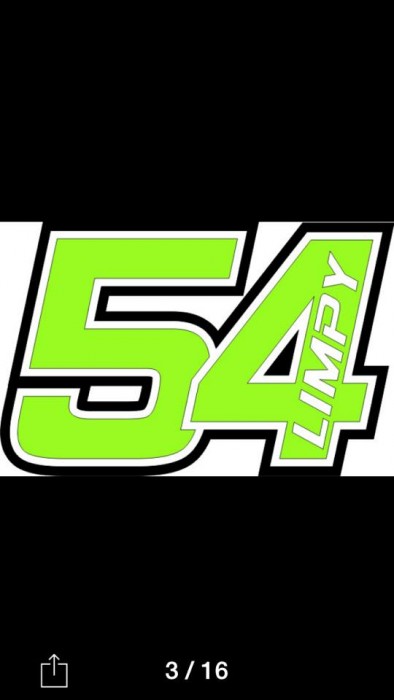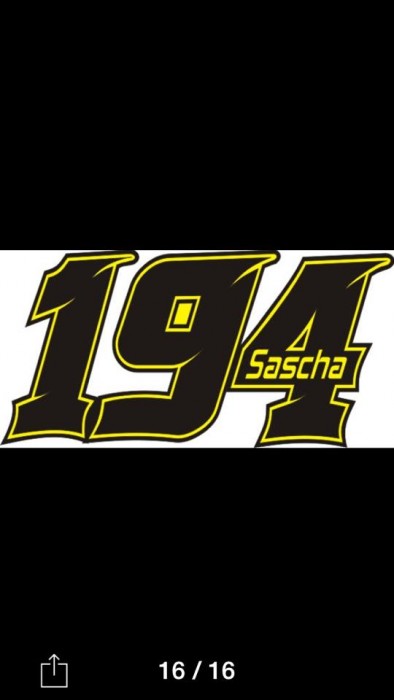
Welche Font :-)
ich habe euch durch das In- Net gefunden und würde gerne eure Hilfe in Anspruch nehmen :-)
Wäre super, wenn ihr mir sagen könntet was das für ein font wäre ?
Leider habe ich das Bild selbst zugeschickt bekommen von einem Kunde. es wird für Racing zwecke verwendet ( Motorrad oder Auto )
Leider kann ich euch keine weiteren Infos geben ;-(
schade das mir keiner Helfen kann.
Das ist kein böser Wille – vermutlich weiß wirklich keiner von uns ad hoc, um was es sich da handelt. Ich würde auf alle Fälle sagen, dass es entweder um zwei verschiedenen Schriftarten sind, oder jemand hat die rechte Schrift von Hand nachbearbeitet, um das linke Resultat zu erzielen (es könnte aber auch einer der unendlich vielen Freefonts sein – in dem Bereich besteht leider keine Chance, den Überblick auch nur ansatzweise zu behalten). Wenn ich mir die rechte Schrift anschaue, dann könnte sie von der Formensprache her in Richtung der Eurostile gehen, bold und kursiv.
Damit Du Erfolg bei der Schriftensuche hast, müsstenst Du die Buchstaben möglichst einzeln ausschneiden und dann in die verschiedenen Identifikationenmaschinen der großen Schriftanbieter füttern.
Hilfreich dürfte auch dieser Artikel hier aus dem Forum sein, der zehn verschiedenen Tricks für die Schriftidentifikation verrät.
also es muss Definitiv eine Schrift sein, da ich jetzt auch andere zahlen mit der Art gesehen habe, es ist soweit auch synchron mit den ecken.
ja leider hast du Recht, Heute zu tage bei sovielen Fonts ist es schier unmöglich :-(
"Sascha" und "54" ist aus der HemiHead 426. Für die "194" müsstest du mal dafont.com durchsuchen, da gibt es so krude Dinge. Kann aber auch sein, dass das eine Schrift ist, die mit einem Folienplotter mitgeliefert wurde und die so nicht auf dem Markt ist. Oder ein Beschrifter hat sie sich von Hand aus einer anderen Schrift hingezupft und verwendet sie für seine Startnummern …
Du könntest auch Wolli vom Bikeroffice fragen, der müsste das wissen.